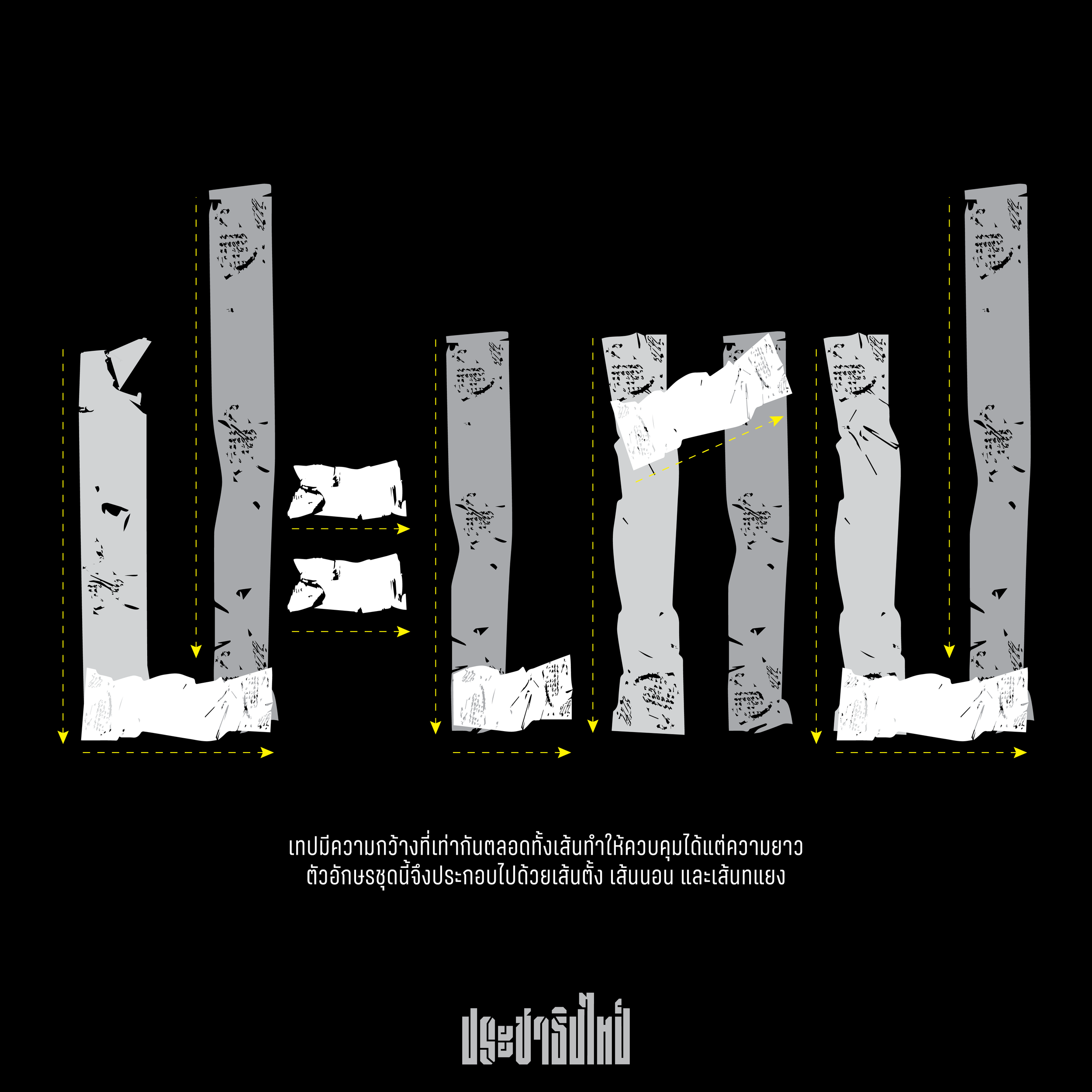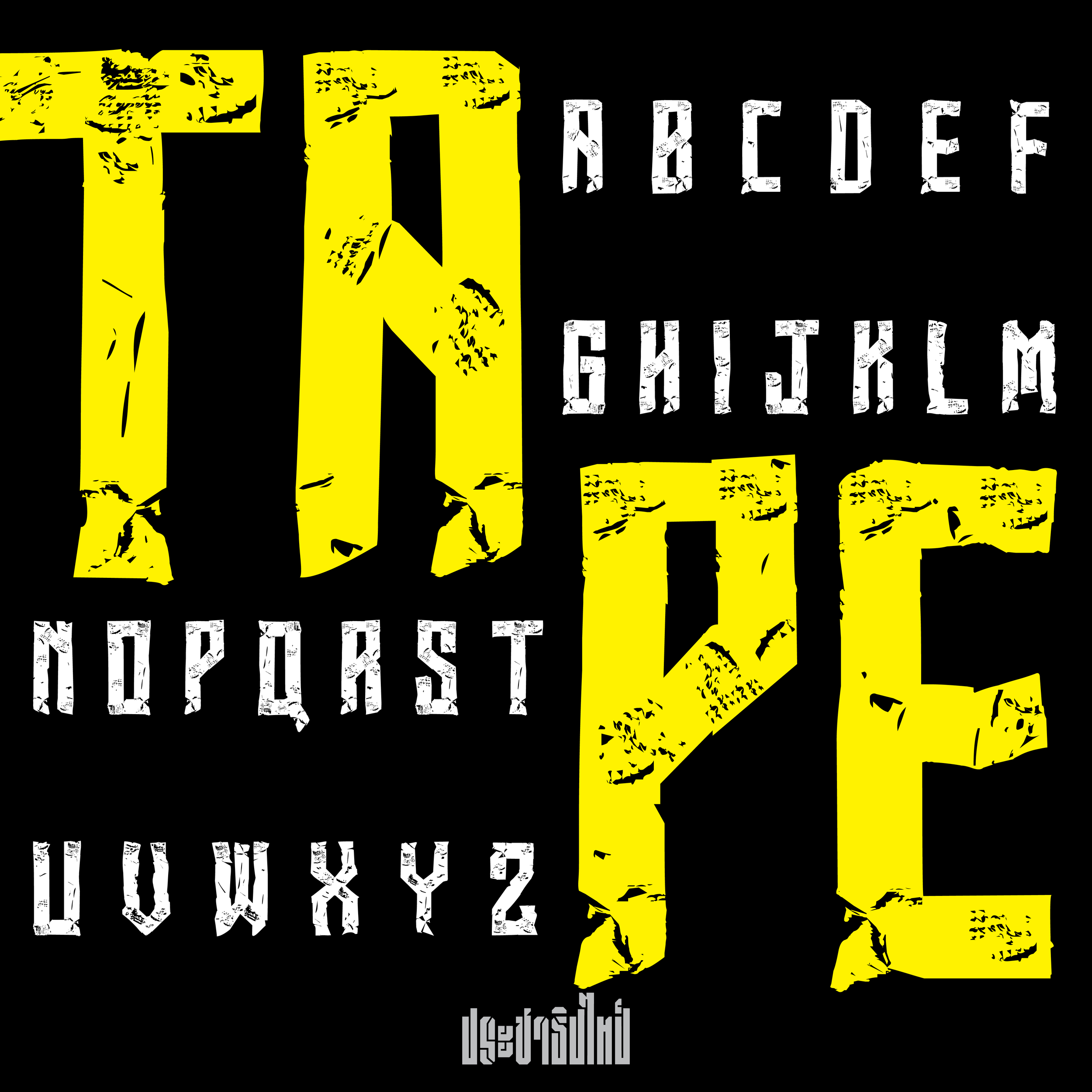
ประชาธิปะเทป
ชุดอักษรประดิษฐ์ และฟอนต์ที่ออกแบบมาเพื่อโปรเจค “บ้านเกิดเมืองนอน” ของ Rap Against Dictatorship เป็นแบบตัวอักษรจากเทปที่มี texture ดิบๆ หยาบๆ ในทรงแคบ (condensed) เพื่อให้ได้น้ำเสียงที่หนักแน่น แหบกร้าน และแข็งกร้าว สอดคล้องกับอารมณ์เพลงที่พยายามสื่อสารความอัดอั้นบีบคั้นของคนรุ่นใหม่ผู้ถูกกดขี่
ความท้าทายของการขยายผลจาก lettering ชื่อเพลง ให้ออกมาเป็นแบบตัวพิมพ์ครบชุด คือการเก็บบุคลิกและลักษณะเด่นของแบบไว้บางส่วน แต่เกลี่ยให้เกิดความเป็นกลางในทุกตัวอักษรจนสามารถใช้พิมพ์ข้อความอะไรก็ได้แล้วยังดูลงตัว
การเดินเส้นของตัวอักษรจำเป็นที่จะต้องเป็นเส้นตรงเท่านั้นเนื่องจากต้องการจำลองธรรมชาติของการทำงานด้วยเทป ถ้าหากจะออกแบบตัวอักษรให้มีความโค้งตามวิธีการเขียนด้วยมือนั้นอาจจะดูเป็นวิธีที่ประดิษฐ์จนเกินไป และขัดกับน้ำเสียงที่ตั้งใจไว้
การกำหนดวัสดุตั้งต้นที่นำมาใช้จึงเป็นทั้งข้อจำกัดและความท้าทายในการออกแบบตัวอักษรชุดนี้ และเนื่องจากเทปมีความกว้างที่เท่ากันตลอดทั้งเส้นทำให้เราควบคุมได้แต่ความยาวเท่านั้น ตัวอักษรชุดนี้จึงประกอบไปด้วยเส้นตั้ง เส้นนอน และเส้นทแยง การเดินเส้นของตัวอักษรจึงไม่สามารถเดินเส้นต่อเนื่องได้ตลอดทั้งตัว แต่เป็นการใช้การประกอบชิ้นส่วนแต่ละเส้นแต่ละมุมจนเกิดเป็นตัวอักษรชุดนี้
สุดท้ายเราเลือกที่จะตั้งชื่อฟอนท์ชุดนี้ว่า "ประชาธิปะเทป" เพื่อสื่อสารถึงรูปลักษณ์ของมันอย่างตรงไปตรงมา และเป็นการระลึกว่าถูกออกแบบขึ้นในขบวนการต่อสู้เรียกร้องประชาธิปไตย
ปกซิงเกิล และชื่อวง
แม้ว่า RAD มีโลโก้วงของตัวเองอยู่แล้ว แต่ในโปรเจคนี้ ทางวงให้อิสระเราออกแบบชื่อวงให้เข้ากับ lettering ชื่อเพลงด้วย เพื่อให้สอดคล้องกับที่ชื่อเพลงมีแถบเทปต่อกันเป็นสามเส้นหยัก เราจึงเลือกใช้องค์ประกอบนั้นกับตัว I ในคำว่า AGIANST เพื่อเน้นความหมายของ “การต่อต้าน”
สำหรับปกซิงเกิล เราเลือกภาพถ่ายจากภาพนิ่งที่บันทึกในการถ่ายทำมิวสิควีดิโอ เพราะฉากของสนามกีฬาที่รกร้าง ประกอบกับธงชาติที่ถูกลดลงครึ่งเสา สามารถสื่อได้ถึงสภาพบ้านเมืองที่กำลังไว้ทุกข์ให้ความย่ำแย่ตามที่กล่าวไว้ในเนื้อเพลงได้อย่างชัดเจน
เรายังไม่หยุด! เรายังไม่ยอม!
ปฏิเสธไม่ได้ว่าเพลงนี้เป็นการโต้ตอบกับเพลงปลุกใจรักชาติสมัยสงครามเย็นชื่อเดียวกันที่ถูกสื่อฝ่ายขวาผลิตซ้ำในปี 2564 การต่อสู้ของประชาชนทั้งในทางตรงอย่างการลงถนน และการทำงานทางวัฒนธรรมผ่านการผลิตสื่อในรูปแบบต่างๆ ที่ท้าทายขนบและความเชื่อเดิมๆ ยังคงดำเนินต่อไป เรายินดีอย่างยิ่งที่ได้มีส่วนร่วมในการเดินทางไกลครั้งนี้ พร้อมกับนำเสนอความเป็นไปได้ใหม่ๆ ในการออกแบบตัวอักษรไทย